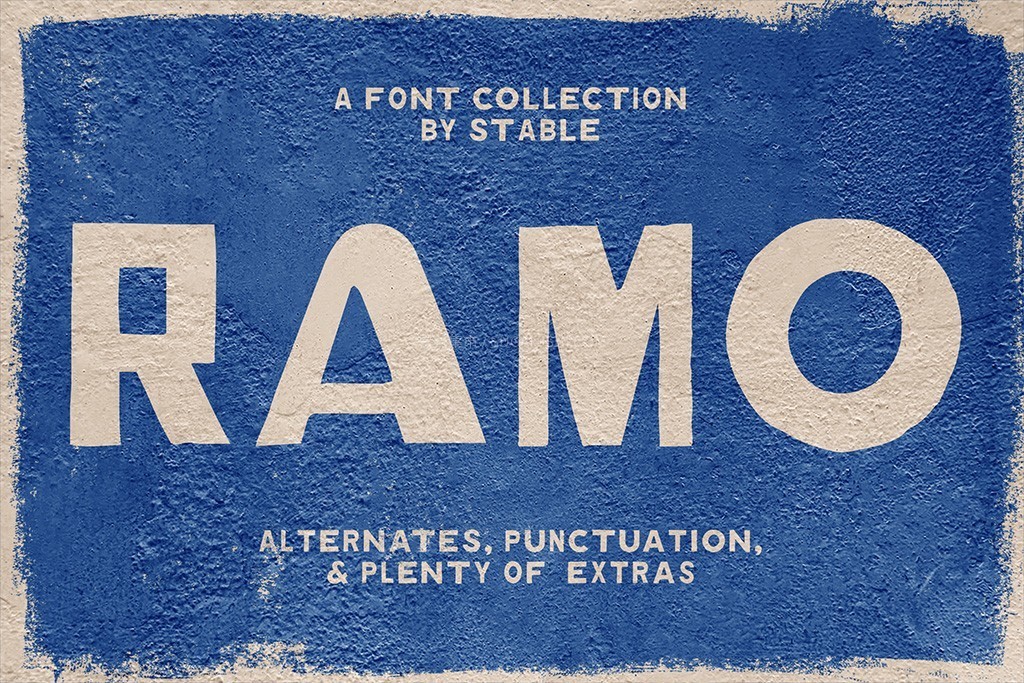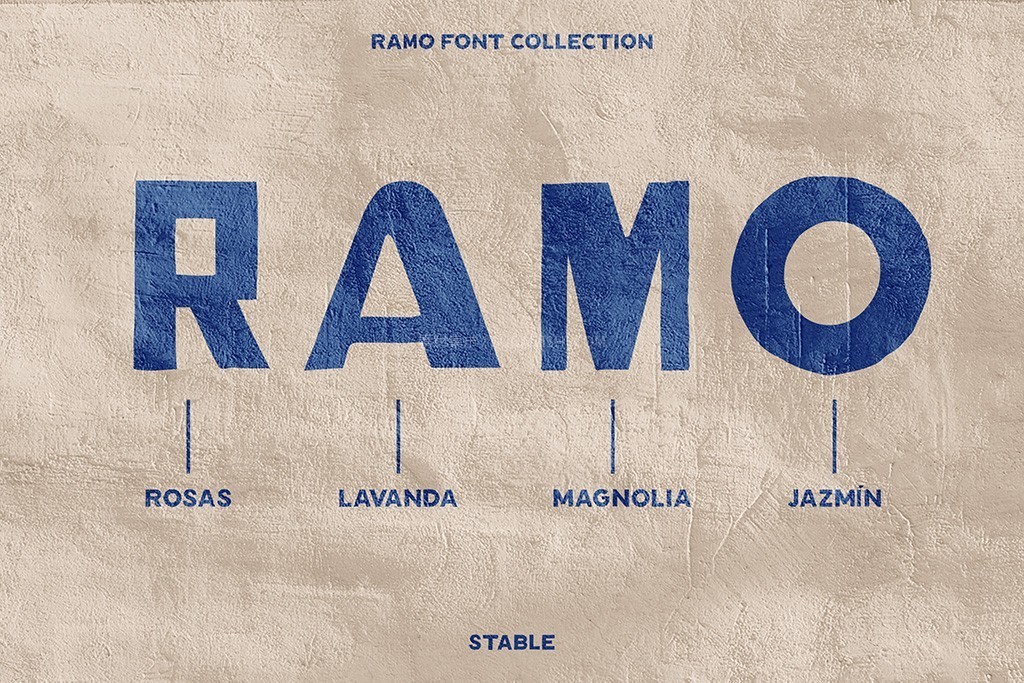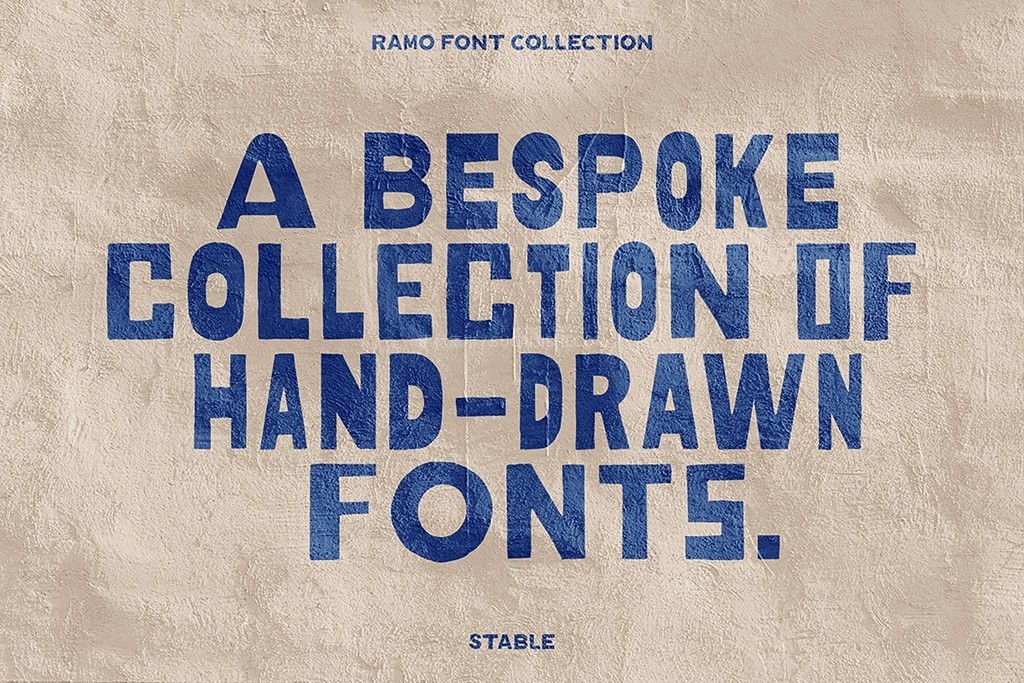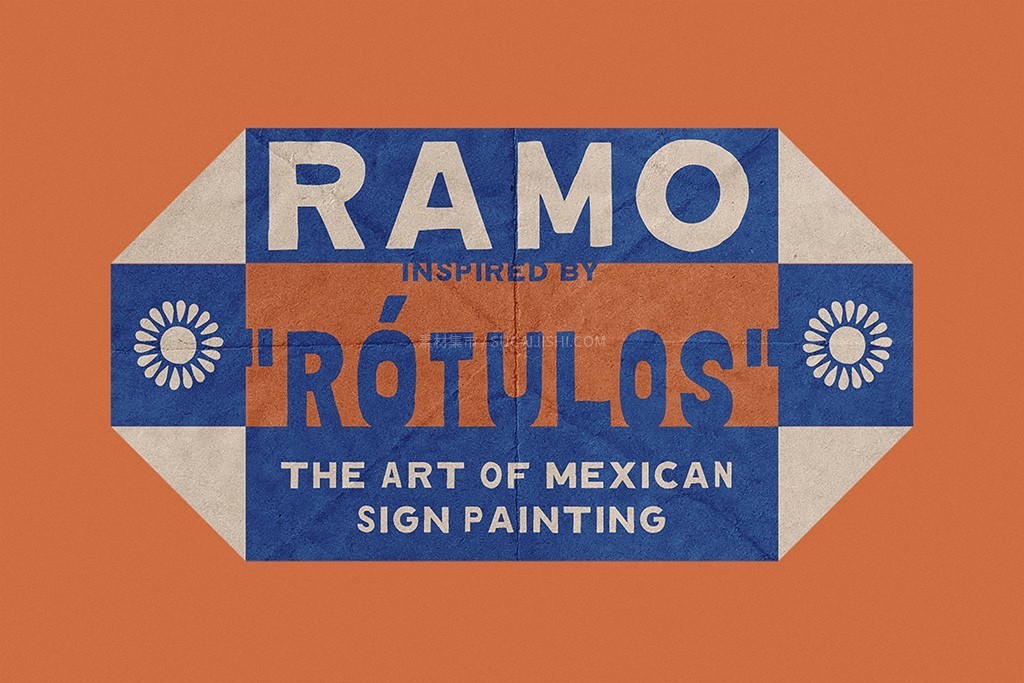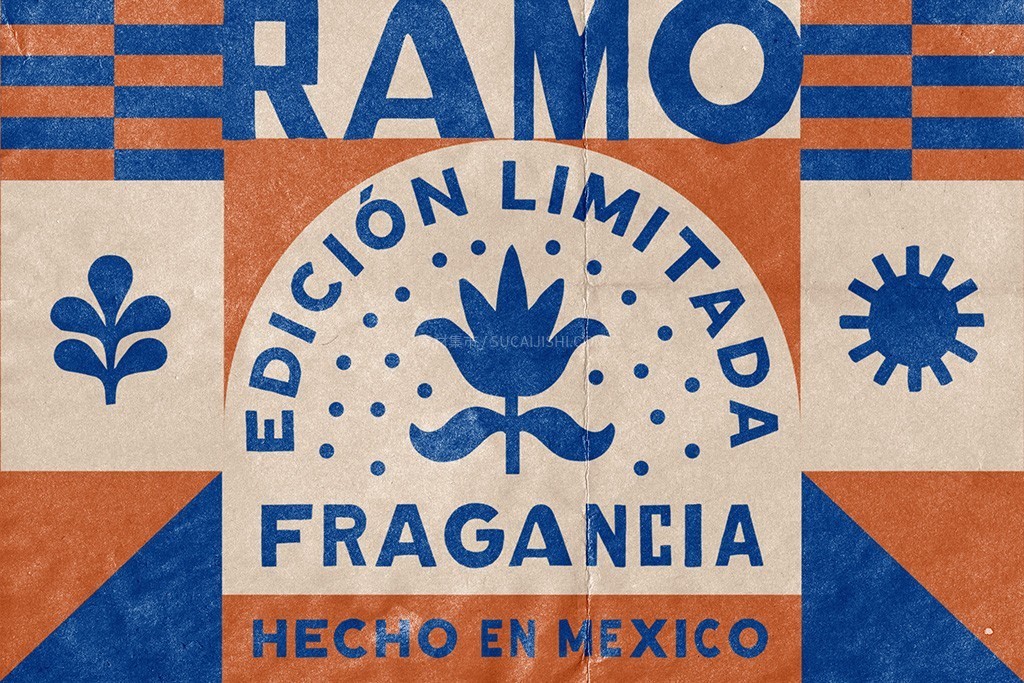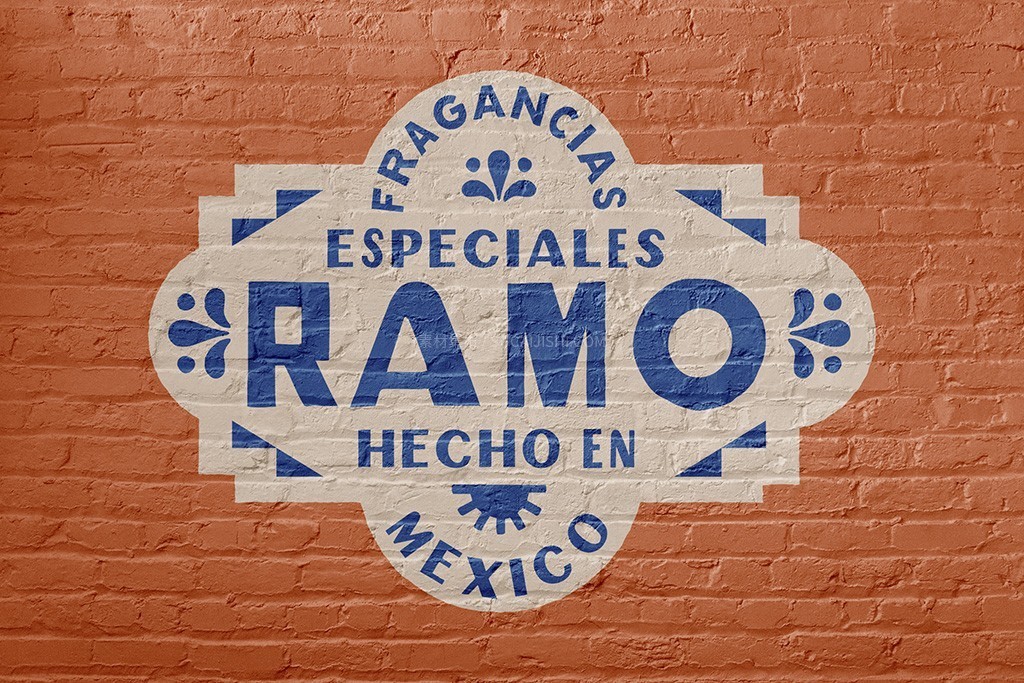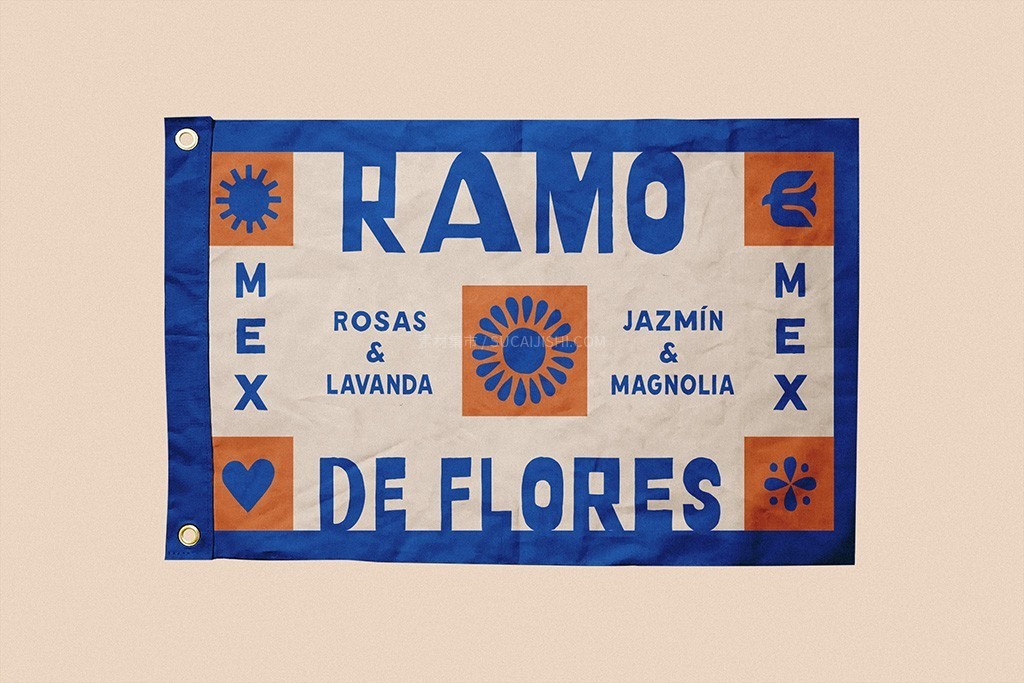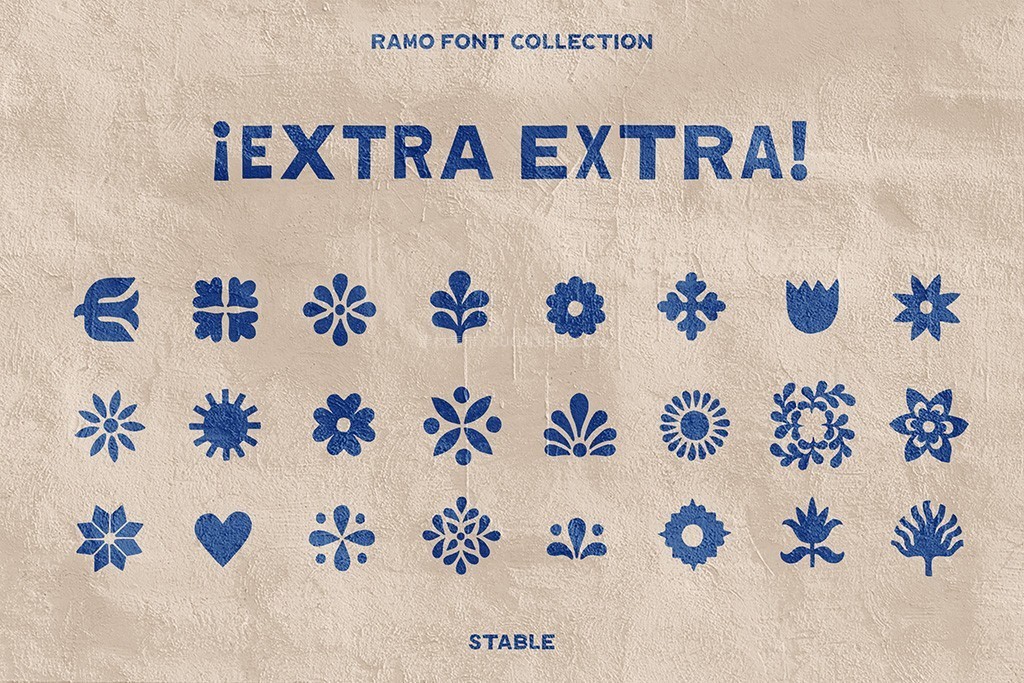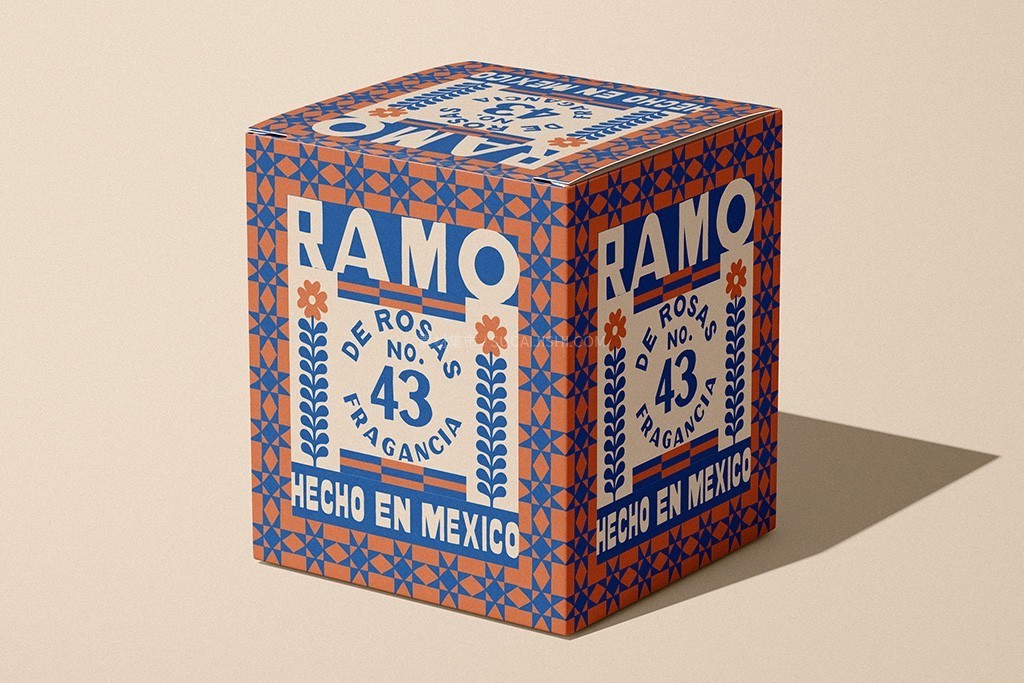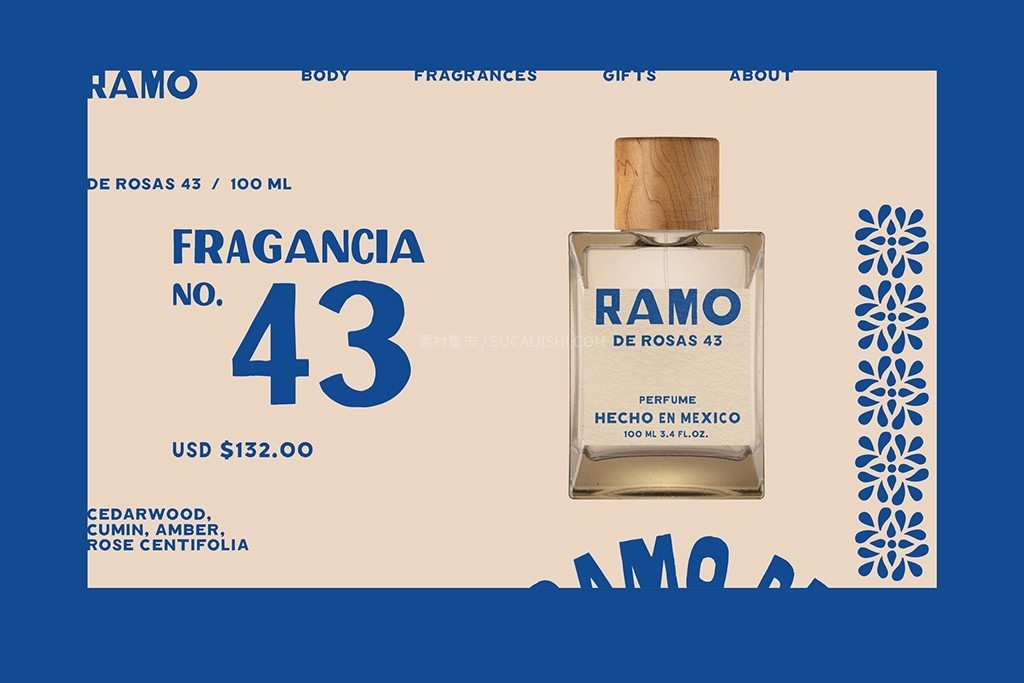
Ramo墨西哥风情手绘招牌字体
Ramo 是一套独具异域风情与复古质感的定制手绘字体。它的设计灵感深刻汲取自传统的墨西哥手绘招牌艺术(Rotulos),极具街头活力与手工温度。该套件包含 4 款不同的字体样式,并全面提供替换字形、数字及标点符号,让排版更加灵活多变。更令人惊喜的是,字体中还特别收录了 20 多个精美的装饰性符号,这些符号的灵感源自经典的墨西哥塔拉韦拉瓷砖。将浓郁的民族特色与手绘艺术完美融合,为你的作品注入独特的视觉魅力。